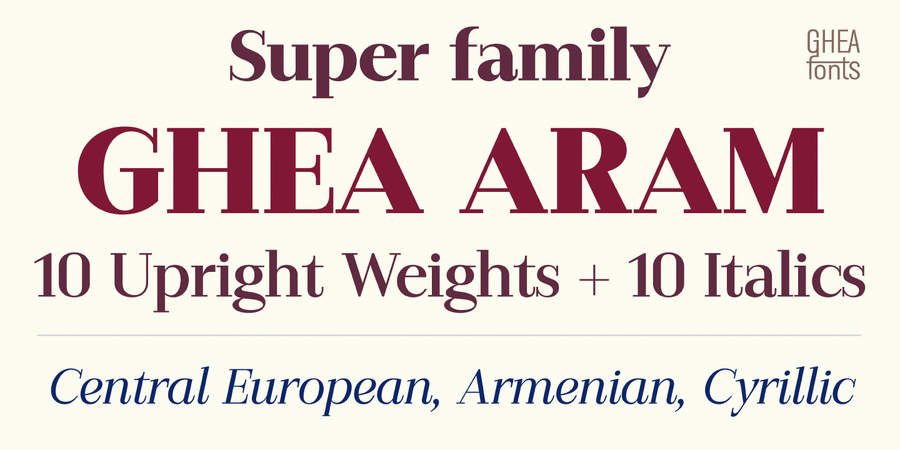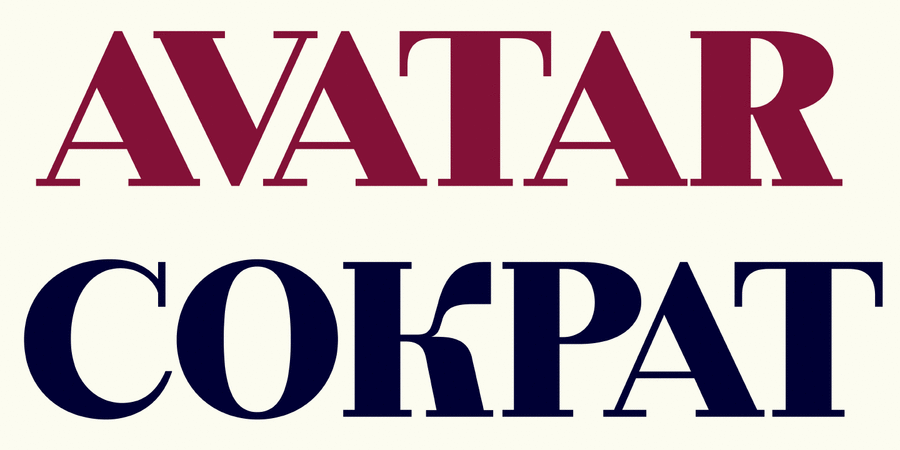
Опис гарнітури GHEA Aram – це багатофункціональна антиква з високим контрастом. Гарнітура містить накреслення для текстового й акцидентного застосування, підтримує латинку, кирилицю та армяницю. Шрифт розробив Едік Габузян у 2018-2021 році.
Асоціації з сімейством шрифтів GHEA AramОсобистість і характер гарнітури:
тонкий, легкий, делікатний, рівний, гармонійний, технічний, сучасний, статичний, культурний, освічений, серйозний, твердий, чіткий, різкий, гострий, розкішний, модний, ювелірний, художній, ввічливий, динамічний, витончений, елегантний, стійкий, ефектний, якісний, елітний, дорогий, багатий, міський, добірний, благородний, красивий, майстерний, естетичний, виразний, пластичний, приємний, акуратний, гнучкий, формальний, стабільний, солідний, гламурний, романтичний, переконливий, класичний, інтелігентний, аристократичний, салонний, урочистий, дзвінкий, вишуканий, музичний, прекрасний, блискучий, знаменитий, дорогоцінний, комільфо, оригінальний, глянцевий, гордий, срібний, сріблястий, театральний, драматичний, творчий, сексуальний, яскравий, тактичний, мотивуючий, авторитетний, значний, важкий, щільний, помітний, активний